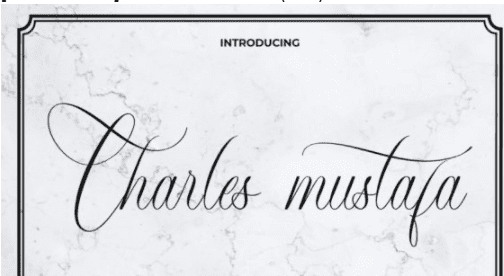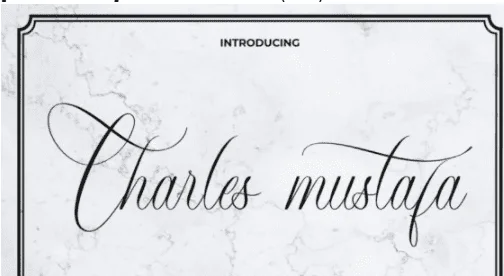
Charles Mustafa - это особый каллиграфический шрифт с изысканными символами, стильным начертанием и великолепными чередованиями. Этот шрифт идеально подходит для приглашений, роскошного брендинга, рекламных акций, песен и многого другого. Charles Mustafa закодирован PUA, что означает, что вы можете легко получить доступ ко всем глифам и штрихам!